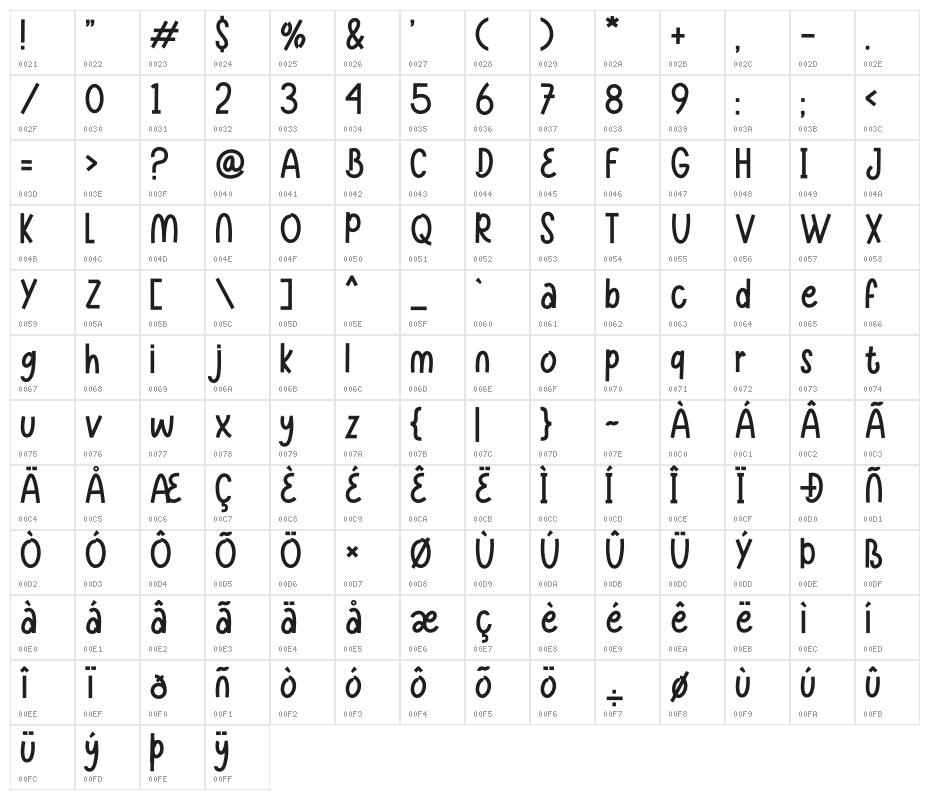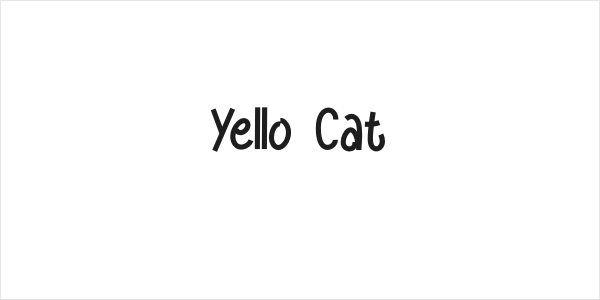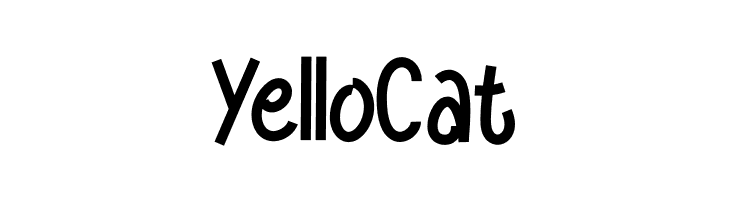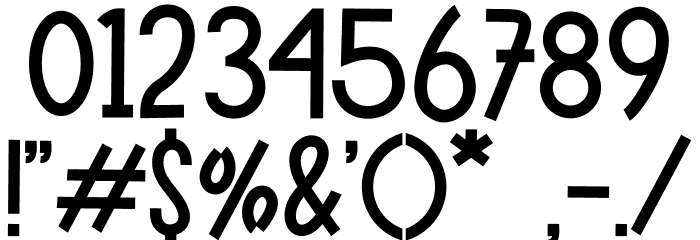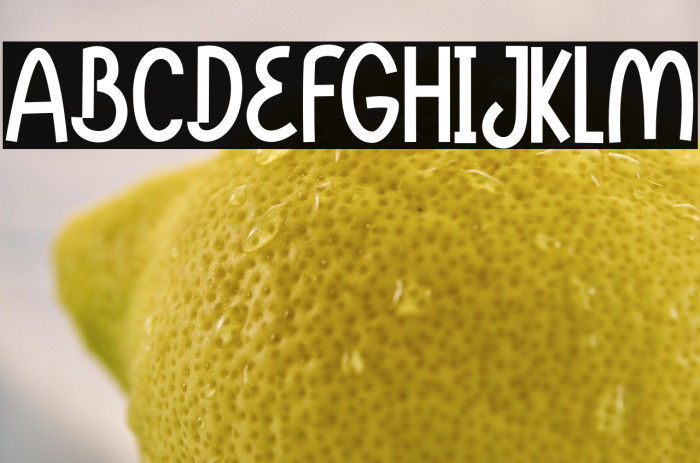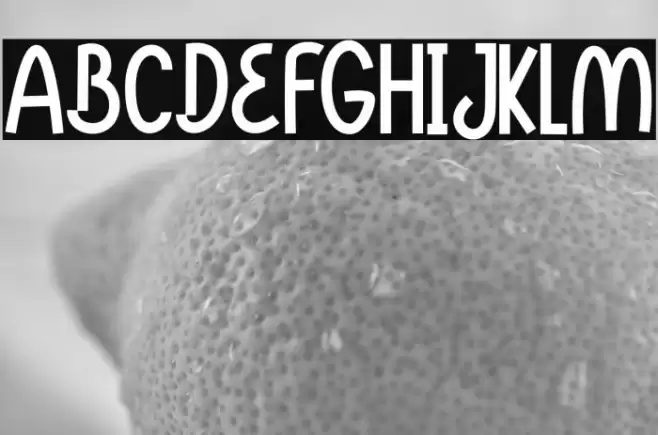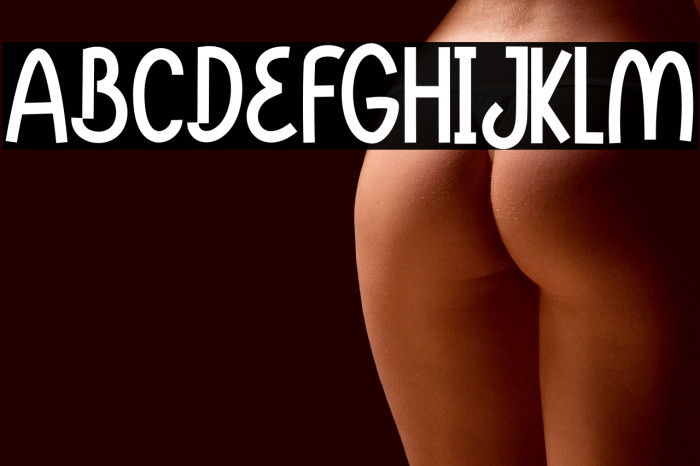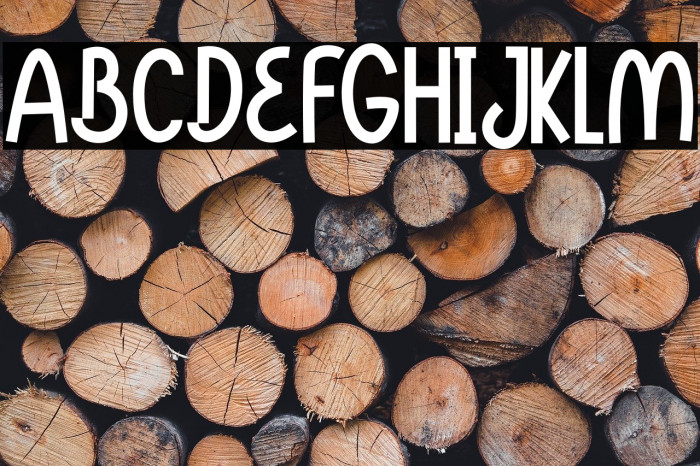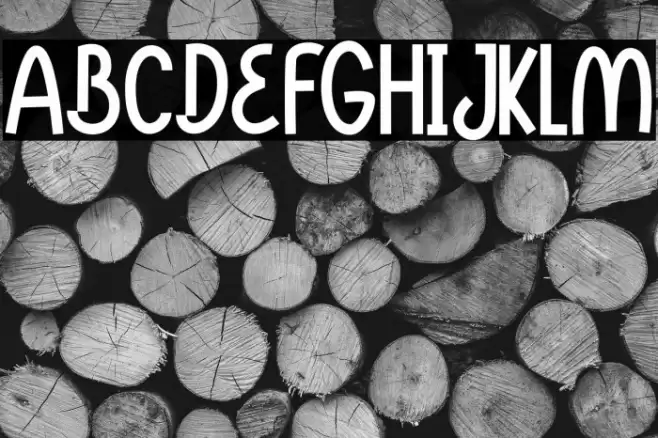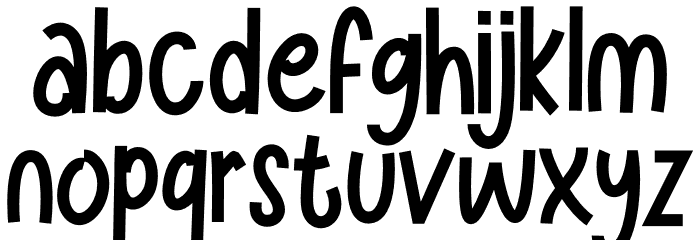
Yello Cat Font
✎ Cartoon
| Catégories | Cartoon |
| Style général | Playful, Whimsical |
| Projets proposés | Ideal for children's books, playful branding, creative posters, and informal invitations. |